Das ewige Buch: Die Bibel
Typografie der Bibel im 20. und beginnenden 21. Jahrhunderten
Bibel und Typografie sind zwei Begriffe, die seit Jahrhunderte miteinander verschränkt sind. Für die Typografie bedeutete das mit dem Beginn des Druckens die »B 42«, die 42-zeilige Bibel, die Johannes Gutenberg in seiner Werkstatt gedruckt und herausgebracht hatte. Seitdem ist die Typografie der Bibel immer wieder Thema von Verlegern und Typografen.
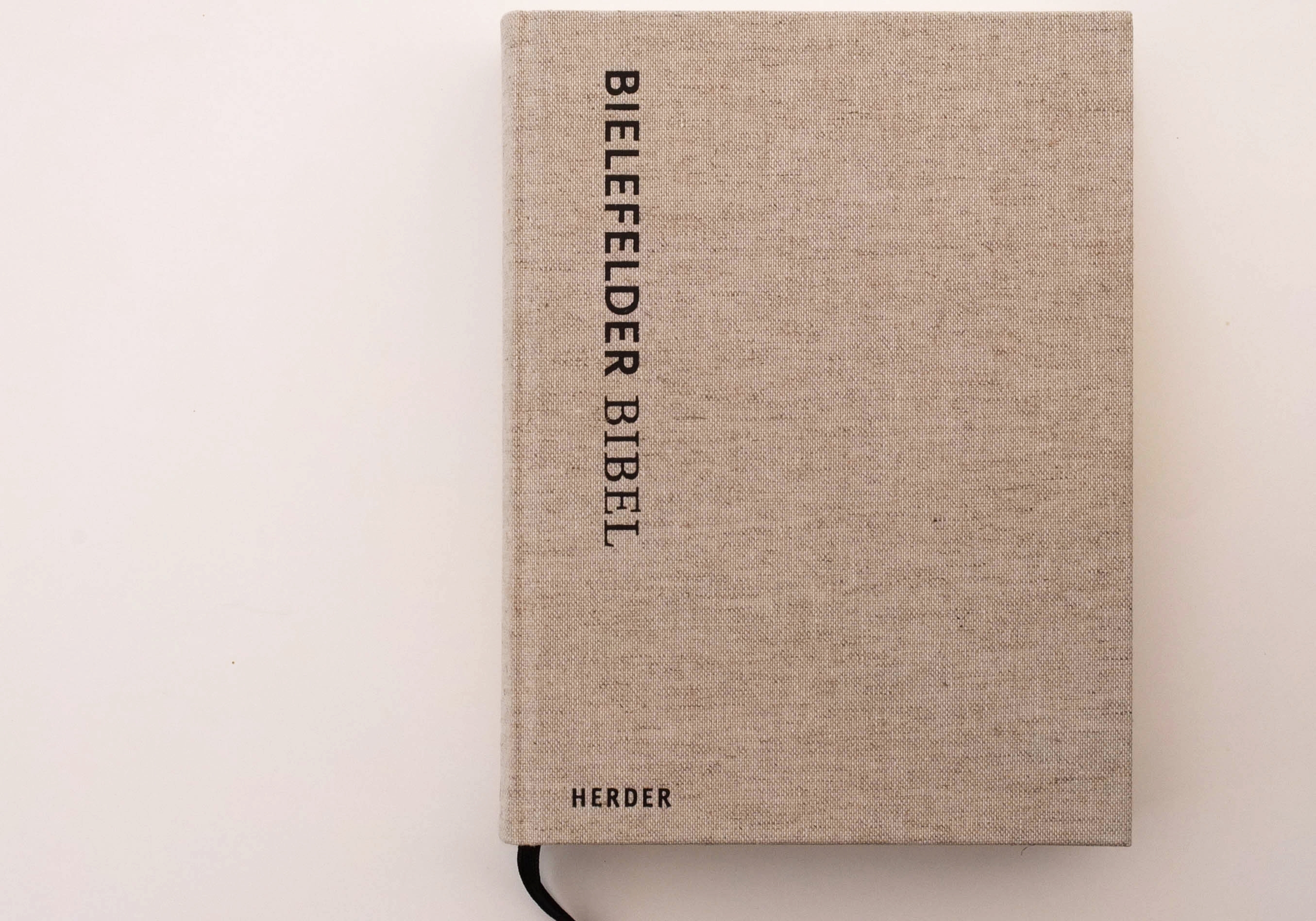
1956 gab es ein großes Ereignis: Bror Zachrisson und Hermann Zapf griffen die Idee Maximilian Vox auf und schrieben an 43 Typografen (es war die Elite der Buchgestalter) die Aufgabe aus, die Bibel neu zu gestalten. Die gedruckten Entwürfe wanderten in Ausstellungen durch die Welt und es wurde eine Mappe mit den Beispielen produziert.
Wenig später, nämlich 1964 schrieb die Württembergische Bibelanstalt einen präzis formulierten Wettbewerb zum gleichen Thema aus. Die Arbeiten wurden weniger bibliophil als die von Stockholm, da auch Anmerkungen und Kommentare gefordert waren. Die Arbeiten wurden in zahlreichen Ausstellungen gezeigt.
2005 präsentierte mein heutiger Gesprächspartner Michael Schlierbach, Studentenpfarrer und Typograf, als Abschluss zum Jahreskurs Typografie ein Werkstattgespräch über die Typografie der Bibel der letzten 20 Jahre. Dabei stellte sich generell ein Mangel in der typografischen Qualität heraus. Selbst bei den Qualitätsanführern von 1964, der Bibelanstalt. Da ich über die Jahre zahlreiche Jugendliche zur Konfirmation mit einer Bibel beschenken wollte, bemerkte ich diese Misere regelmäßig.
Schlierbach hatte mich auch auf die Zürcher Bibel aufmerksam gemacht. Die ist – in diesem Bereich ganz ungewöhnlich – im Flattersatz gesetzt. Die Schrift (Schrift und Gestaltung Christoph Noordzij) erscheint mir aber im Verhältnis zum Zeilenabstand zu groß. Wobei sicher vom Gebrauch her und der zu erwartenden Leser einiges für die Schriftgröße spricht.
Natürlich gibt es immer auch die Versuche, alles anders zu machen um das Interesse an der Bibel anzufachen. Bibel als Bildband, als Comic oder als Magazin, jedenfalls in der Art der Gestaltung. Auf der Qued 2016, einer Tagung zur Magazingestaltung in München, führte Andreas Wurm sein mit Andreas Volleritsch gestaltetes Neue Testament vor. Hier sind alle sachlich-typografischen Register einer interessanten Magazingestaltung gezogen.
Im folgenden Text finden Sie meine Eindrücke zur Bielefelder Bibel, aber auch zur Bibel als Magazin. Im anschließenden Beitrag kommentiert Michael Schlierbach die Bielefelder Bibel aus seiner Sicht als Theologe und Typograf, eine Kombination, die eher selten vorkommen dürfte.
Bielefelder Bibel
Über die Bielefelder Bibel hatte ich im tgm-Blog über eine Vorstellung des Projektes auf der typo Berlin 2014 berichtet. Meine damalige Faszination hat sich jetzt mit der vorliegenden fertigen Ausgabe noch verstärkt. Die literarische Vielfalt der Bibel (welche sehr komplex ist, wie man bei Martin Urbans Geschichte der Bibel nachlesen kann) wird in der typografischen Kennzeichnung der Textsorten betont. Die Schriftwahl mit der Nexus von Martin Majoor empfinde ich als ausgesprochen glücklich.
Nach wiederholter Durchsicht des Buchkomplexes fällt mir auf: Die einzelnen Textteile der Bibel werden sehr unterschiedlich behandelt und man bemerkt den Studiocharakter des Bibel-Projektes. Einige Texte sind höchst sensibel und auch originell typografisch umgesetzt. Andere unterscheiden sich so, dass nur Typografen oder dementsprechend geschulte Personen Unterschiede bemerken können. Doch ist damit und vielleicht auch gerade dadurch der Anreiz zum Lesen hoch. Und vielleicht gilt das besonders für Leser, die nicht gewohnt sind, in einer konventionell gesetzten Bibel zu lesen.
Die Genesis beginnt mittelachsig. Das kommt sehr feierlich herüber. Es ändert sich mit der »Erschaffung der Welt«, die zunächst einen breiten Satzspiegel erhält, mit hohem Fußsteg. Dazwischen werden »Israel und die Völker« (S. 31) mit großem Durchschuß gesetzt werden und der Satzspiegel wird nach unten erweitert.
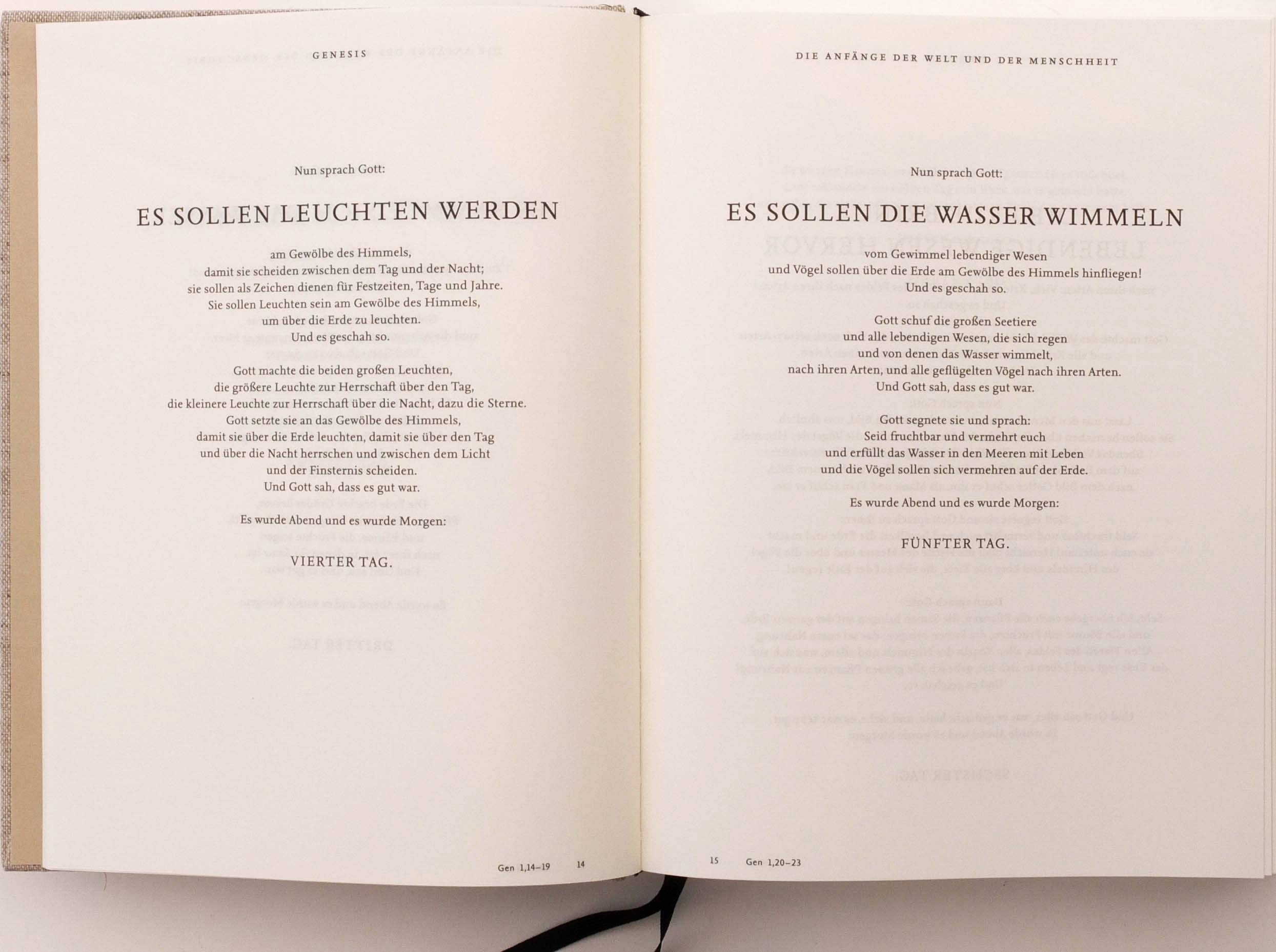
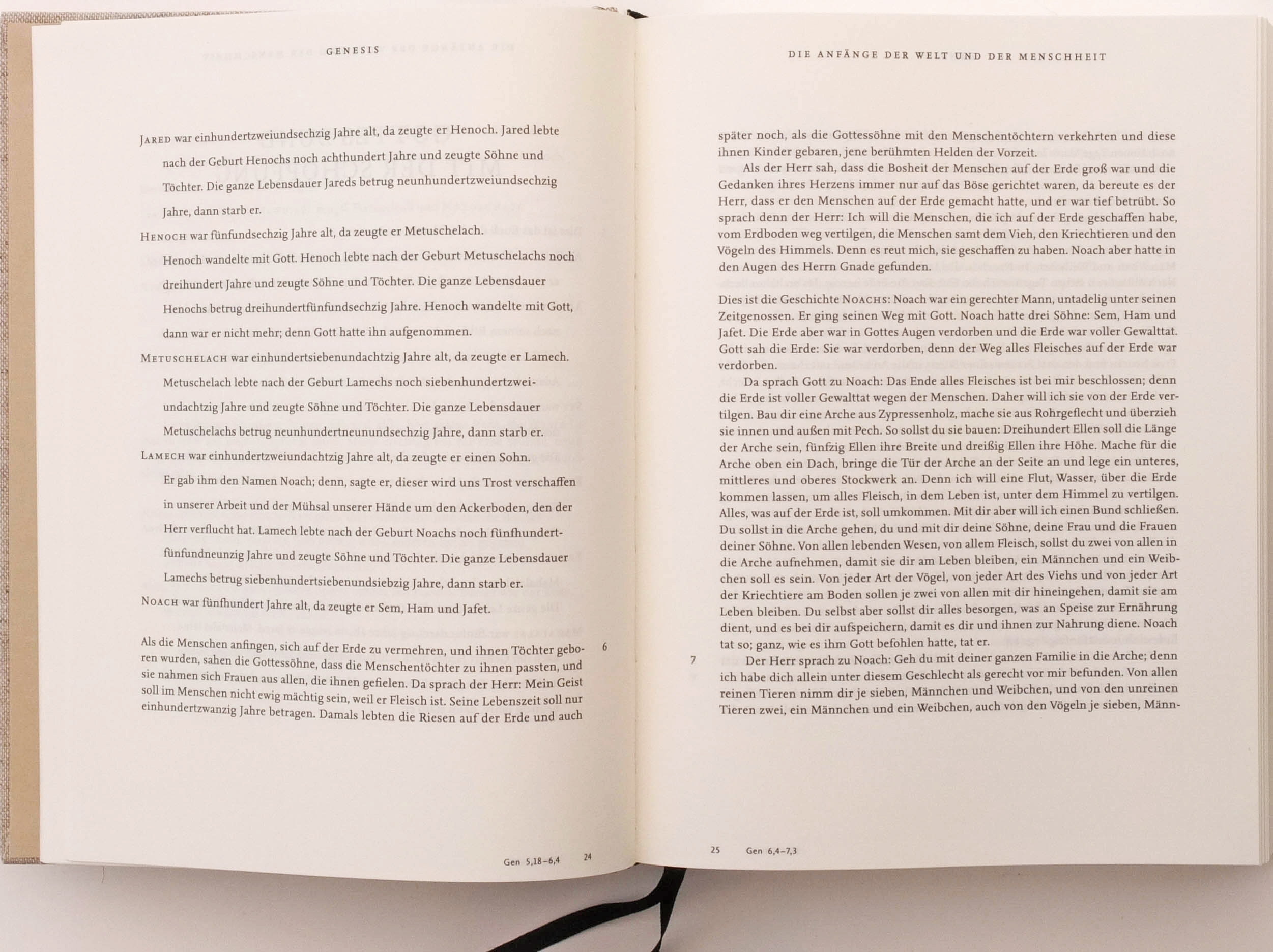
Die rechtsseitigen Zwischentitel sind jeweils den folgenden Kapiteln angepasst. »Jakob und seine Söhne« wirken durch seinen Satzspiegel elegant und ruhig, eben wie gut gesetzte Belletristik. Natürlich werden Besonderheiten im Text wie die Aufzählung von Namen auch typografisch fein hervorgehoben (S.93).
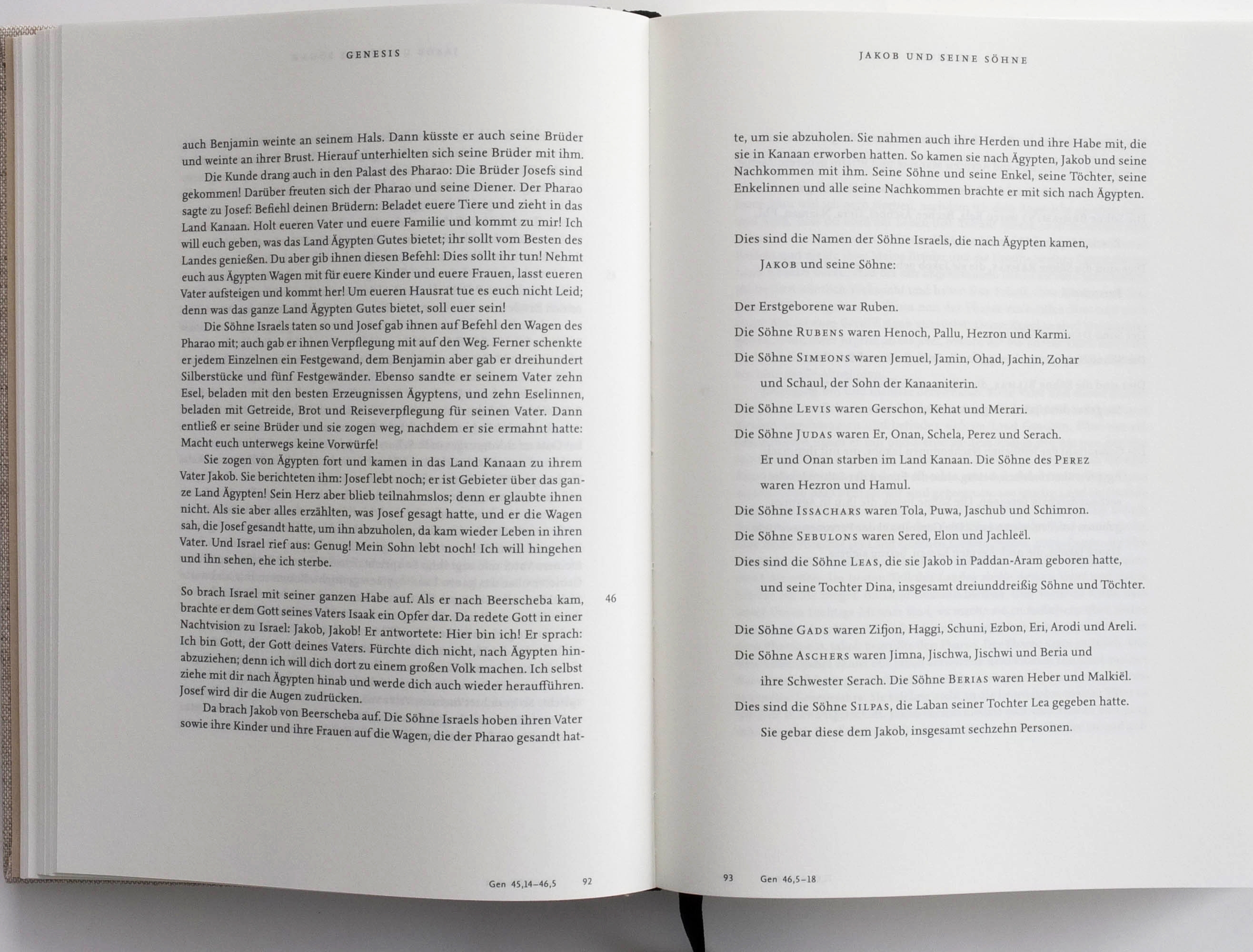
Ähnlich, aber in der Spannung nach unten, erscheint der »Exodus«. Die Lieder sind dabei als Gedichtsatz in Kursiv gesetzt (S. 131). Unterüberschriften und Marginalien stehen gut in der Wirkung zum Grundtext.
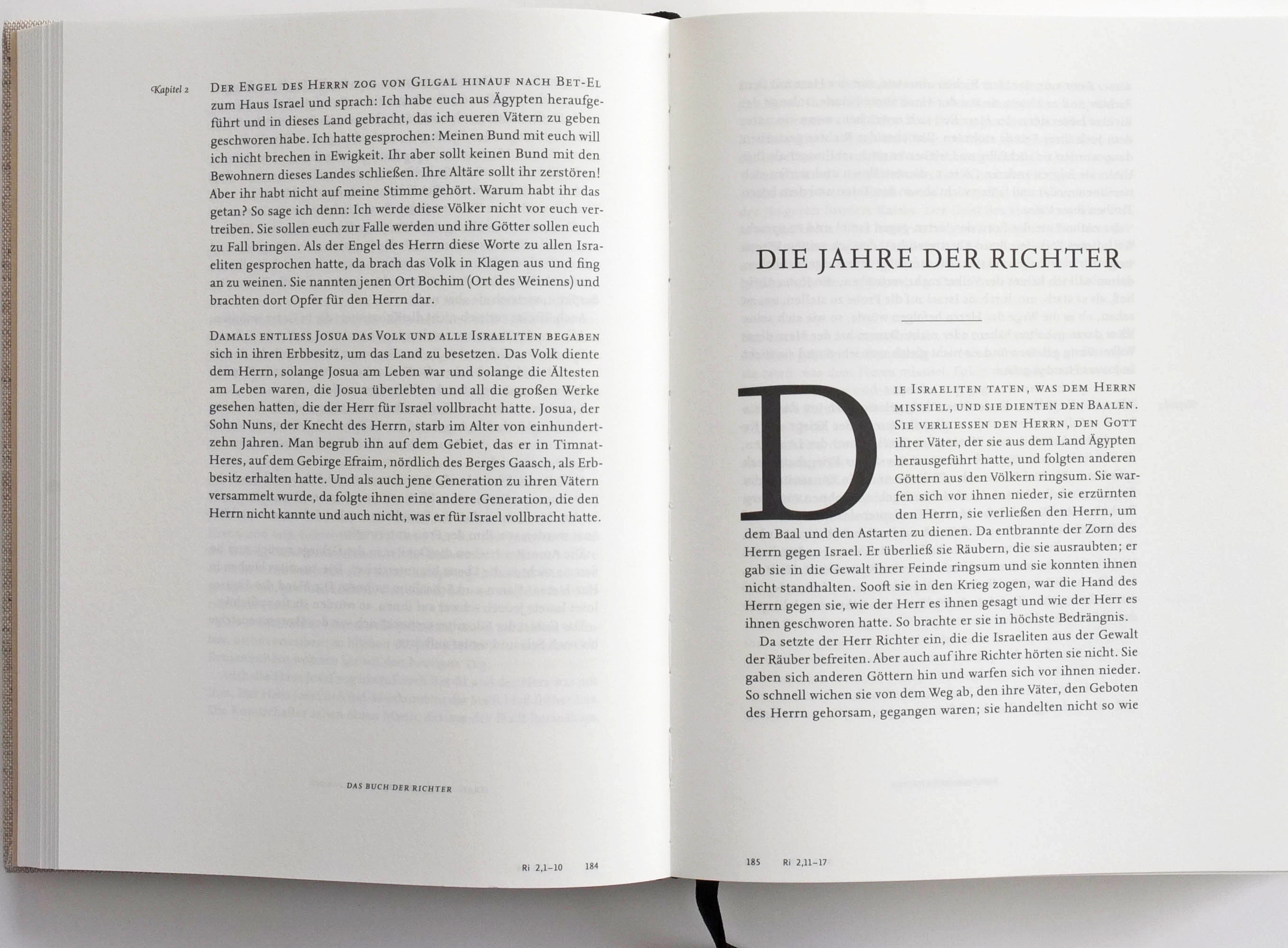
Im »Buch der Richter« (S. 185) wird der Satzspiegel wieder in guter Konvention sehr angenehm. Der Kolumnentitel wird hier zum Fußtitel. Die Initialen sind aber zu groß und damit laut. Das wird noch heftiger in »Michas Heiligtum und die Daniter«. Acht Zeilen hohe Initialen erinnern dann mehr an Altarbibeln. Hierbei ist der Satzspiegel seitlich verschoben, der breitere Steg ist immer links.